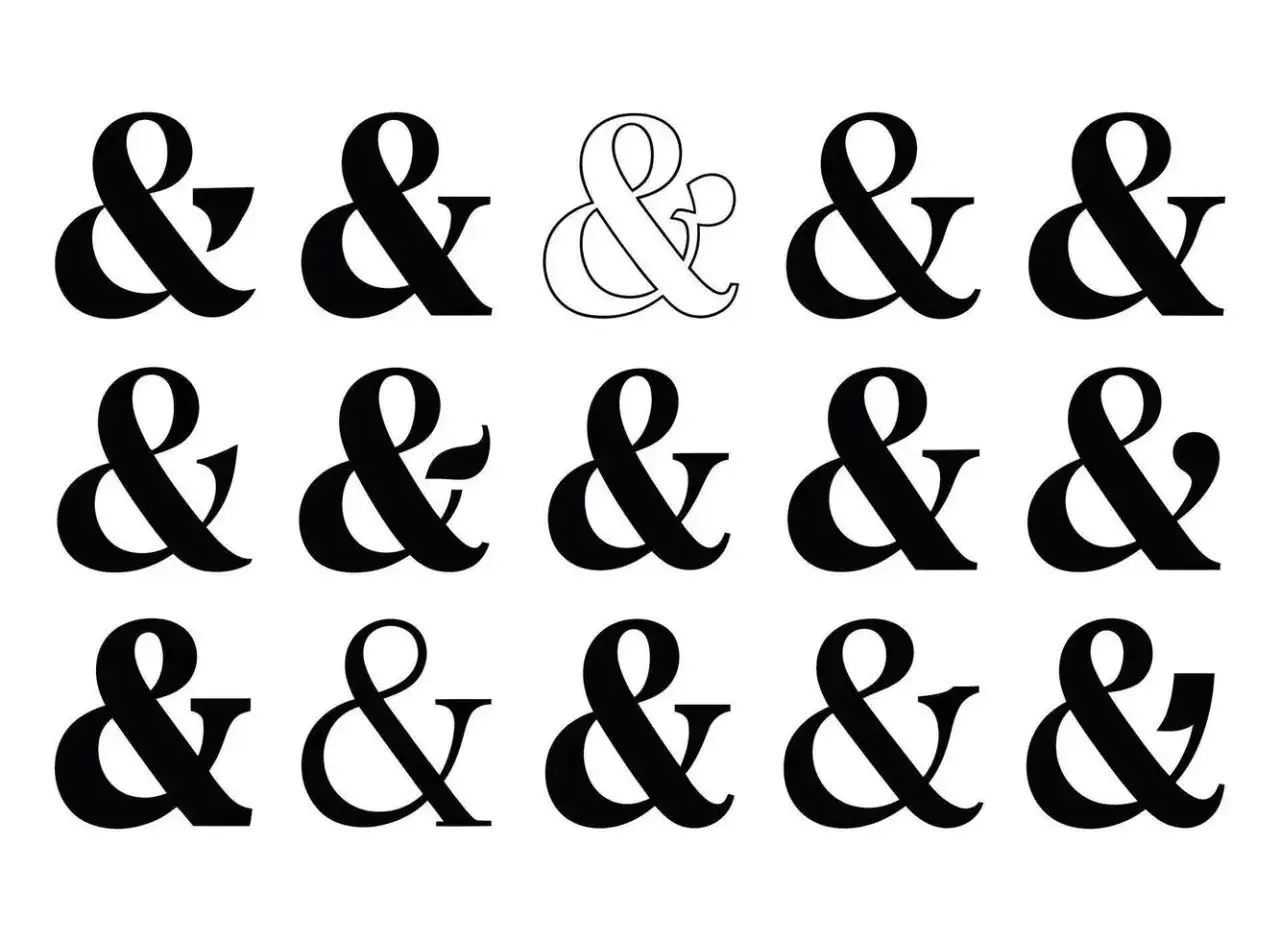
Y comercial - significado y usos en tipografía y diseño
Diseños tipográficos variados, incluyendo el **símbolo y** en "The Knee Amigos". A la derecha, la palabra "Efficiency" formada por una manguera y una boquilla de surtidor.
La y comercial, representada por &, es un recurso pequeño con bastante peso visual: puede unir nombres, acortar titulares y dar a una composición un tono más cuidado. En tipografía no funciona solo como atajo de la palabra “y”; también transmite ritmo, jerarquía y carácter. Aquí vas a encontrar qué significa realmente, cuándo conviene usarla y qué decisiones tomar para que no estorbe en un logotipo, una portada o un texto digital.
Lo esencial de la y comercial en una lectura rápida
• El signo & representa la conjunción “y” y nace como una ligadura histórica del latín et.
• En identidad visual funciona mejor cuando forma parte del nombre, no cuando se añade por puro adorno.
• Su personalidad cambia mucho de una tipografía a otra: puede verse clásica, técnica, elegante o informal.
• En diseño digital hay que vigilar su tratamiento en HTML, porque es un carácter reservado en el código.
• El mejor criterio no es usarla más, sino usarla cuando aporta claridad, ritmo o carácter.
Qué es realmente la y comercial
Yo la trato como una pieza híbrida: no es una letra, pero se comporta como si tuviera carácter propio. Su origen suele explicarse como una ligadura del latín et, y de ahí viene su capacidad para condensar dos ideas en un solo signo. En diseño editorial y branding eso importa mucho, porque un símbolo así no solo conecta palabras; también define el tono de la pieza.
En la práctica, conviene leerla en tres niveles: como signo, como forma y como recurso expresivo. Esa triple lectura ayuda a no confundirla con una simple decoración tipográfica.
Nombre Qué significa Por qué importa
Ligadura Une dos formas en una sola Explica su origen visual y su evolución tipográfica
Logograma Representa una palabra completa Por eso puede sustituir a “y” sin perder sentido
Y comercial Uso práctico en nombres, marcas y composiciones Le da una función editorial y comercial muy concreta
Cuando entiendo esto, me resulta más fácil decidir si el signo suma o si solo ocupa espacio visual. Y esa distinción es justo la que marca la diferencia entre usarlo con criterio o meterlo donde no toca.
Con esa base, ya tiene más sentido ver en qué contextos aporta valor y en cuáles estorba.
Cuándo conviene usarla y cuándo no
La decisión no es decorativa, sino estratégica. Yo la uso cuando el nombre, el título o la composición ganan claridad y ritmo con el signo, y la evito cuando la lectura necesita ir fluida y sin interrupciones. Si trabajas con textos para web, identidad o papelería, esta diferencia te ahorra bastantes errores.
Contexto ¿La usaría yo? Motivo
Nombre de marca Sí, si forma parte real del nombre Respeta la identidad y refuerza el reconocimiento
Titulares cortos A veces Ahorra espacio y puede dar un ritmo más editorial
Texto corrido Normalmente no La palabra “y” suele leerse con más naturalidad
Etiquetas y fichas Sí, con moderación Condensa información sin perder claridad
Documentos formales Solo si el estilo lo exige Prima la consistencia normativa y la lectura directa
HTML y maquetación web Sí, pero bien codificada En código debe escribirse como & para que se interprete correctamente
La regla práctica es simple: si el signo aporta una relación clara entre dos elementos, suma; si solo busca parecer moderno, suele estorbar. Esa frontera se ve mejor cuando observas cómo cambia según la familia tipográfica.
Una cuadrícula de símbolos
Qué cuentan sus formas en una tipografía
Cada familia tipográfica dibuja este signo de una manera distinta. Yo suelo fijarme en cuatro cosas: apertura, contraste, equilibrio con las letras vecinas y comportamiento en tamaños pequeños. Un ampersand muy cerrado puede verse elegante en una portada, pero apagarse en una interfaz; uno demasiado ornamental puede ser memorable en un logotipo y, al mismo tiempo, romper la lectura en una etiqueta o un pie de foto.
• En serif clásicas, suele verse más caligráfica y con un aire editorial que funciona bien en libros, invitaciones o marcas con un punto artesanal.
• En sans serif modernas, tiende a simplificarse y gana neutralidad, algo útil en interfaces, señalética o identidades limpias.
• En tipografías display, puede volverse protagonista y aportar mucha personalidad, pero exige más control para no competir con el nombre.
• En estilos manuscritos, comunica cercanía y movimiento, aunque a veces sacrifica legibilidad si el tamaño es pequeño.
Yo lo miro casi como un mini test de la familia tipográfica: si el signo encaja con el resto de las letras, la fuente está bien resuelta; si parece venir de otro sistema, conviene revisar la elección. Un buen detalle no debe romper la armonía general.